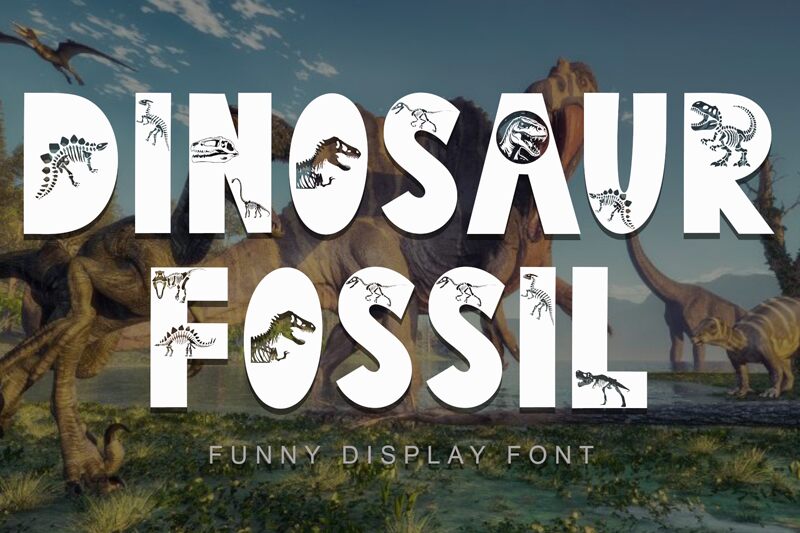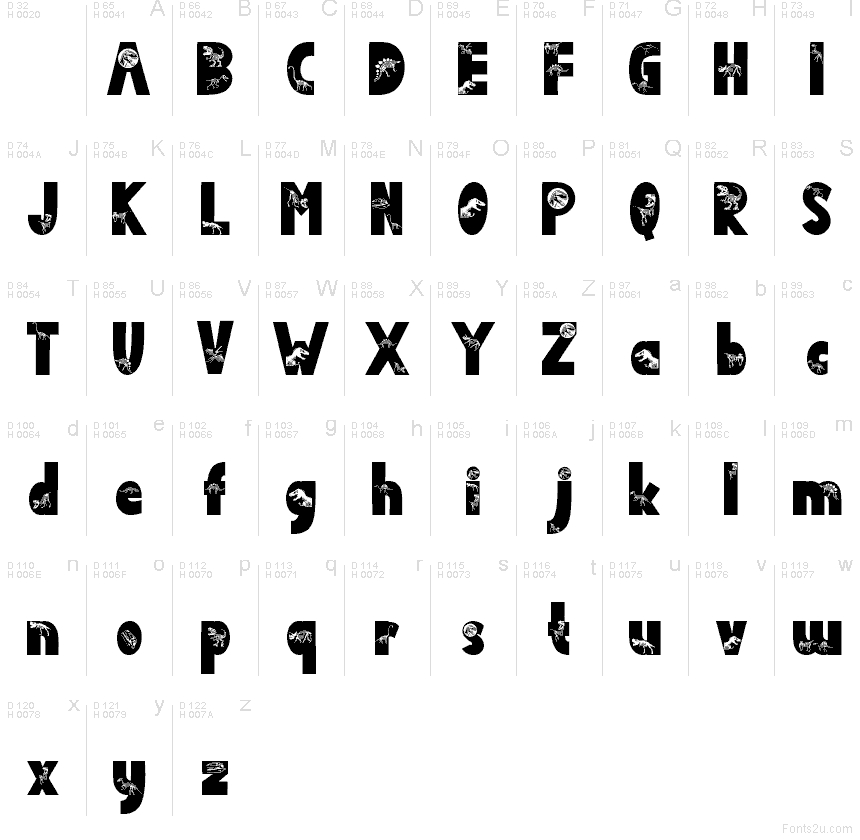
Dinosaur Fossil
Dinosaur Fossil, créée par Yoga Letter, est une police d'affichage gratuite dont les formes arrondies et audacieuses sont ornées de figures de dinosaures, de crânes et d'empreintes de fossiles. Avec son allure de présentation muséale gravée, chaque caractère remplace les traits classiques par des motifs préhistoriques.
Dinosaur Fossil est idéale pour les livres pour enfants, la signalétique de musées, les affiches scolaires, les invitations de fêtes et les emballages à thème, car ses détails fossiles confèrent à chaque mot une véritable touche jurassique. Cette police gratuite est également parfaite pour les logos, les bannières d'événements et les titres décoratifs lorsque vous souhaitez que le lettrage incarne pleinement le thème des dinosaures.